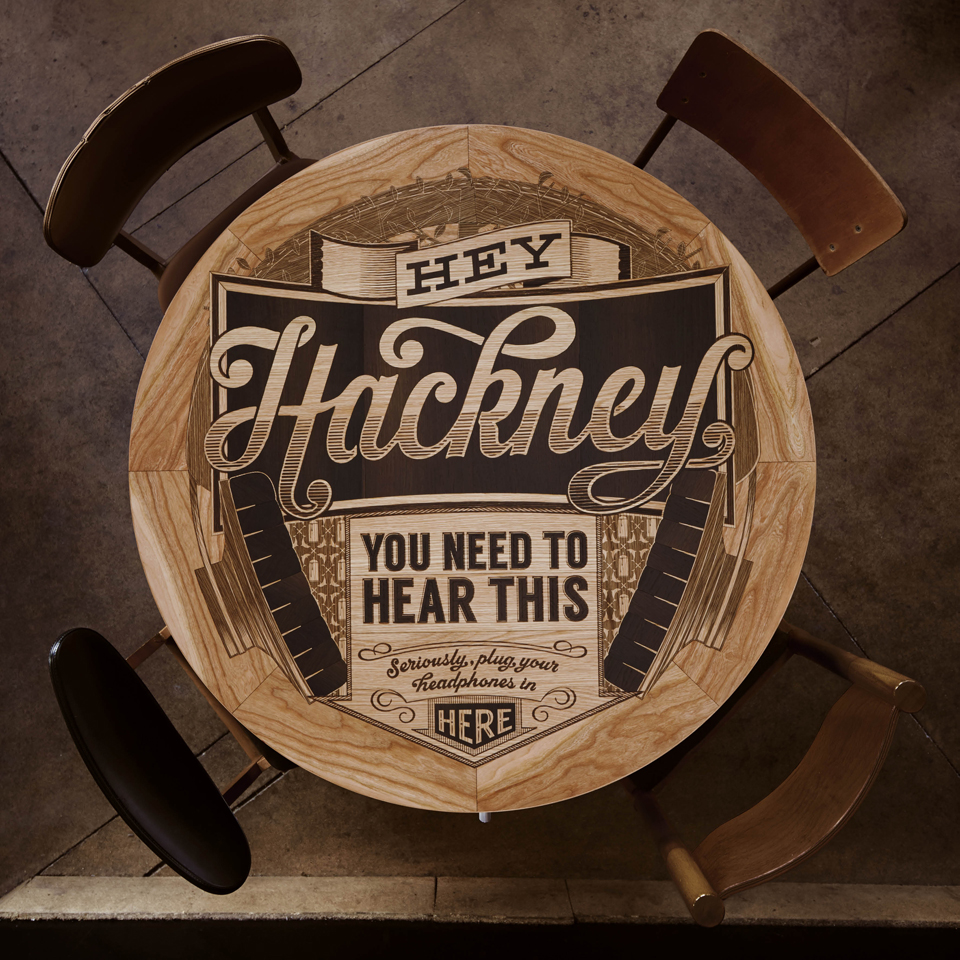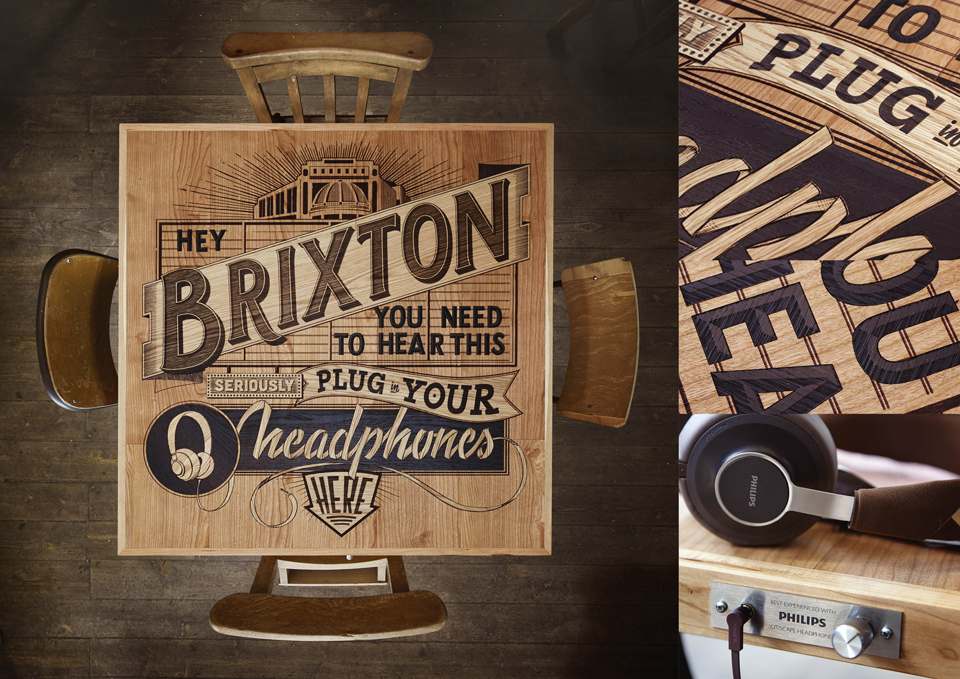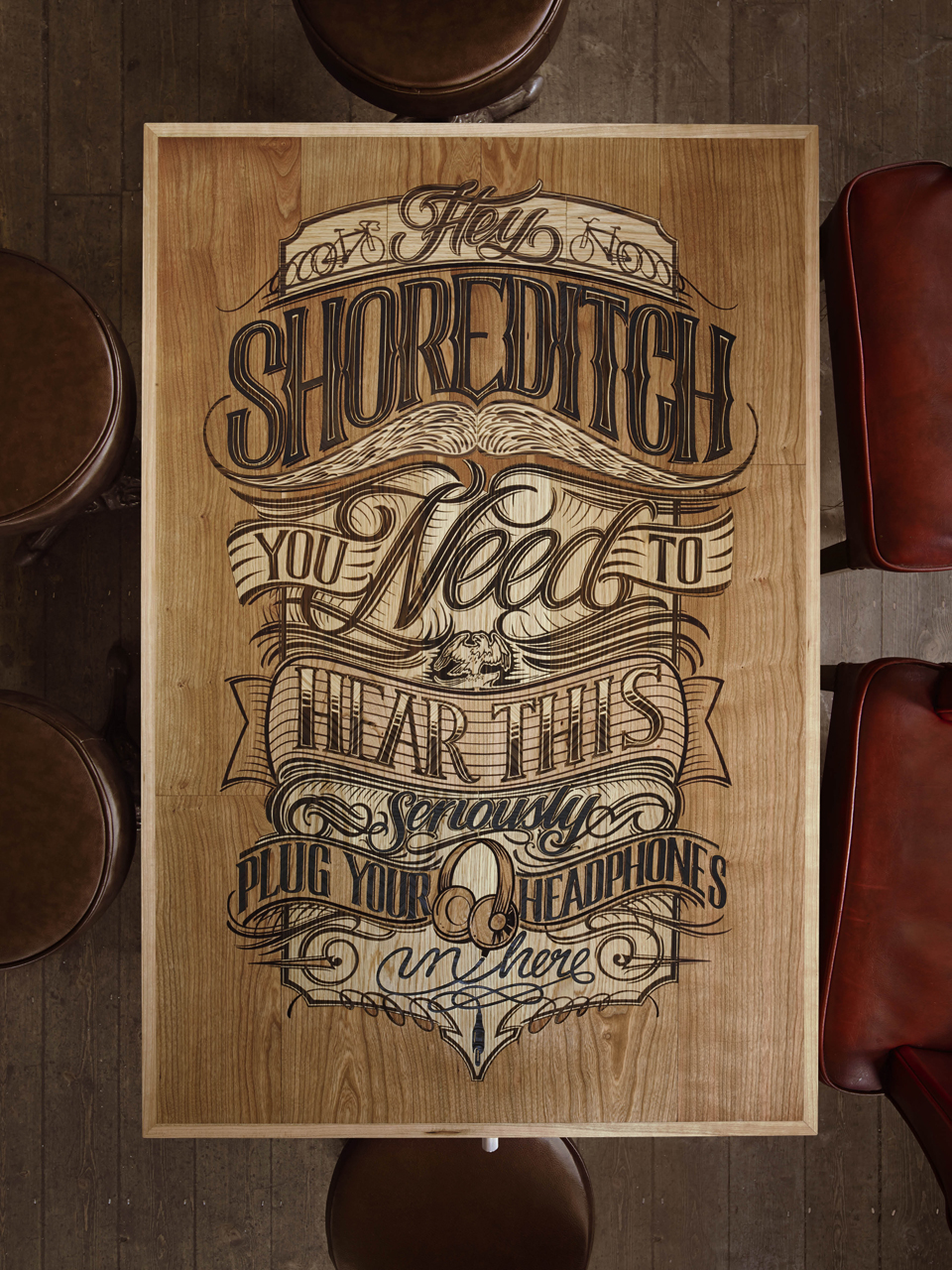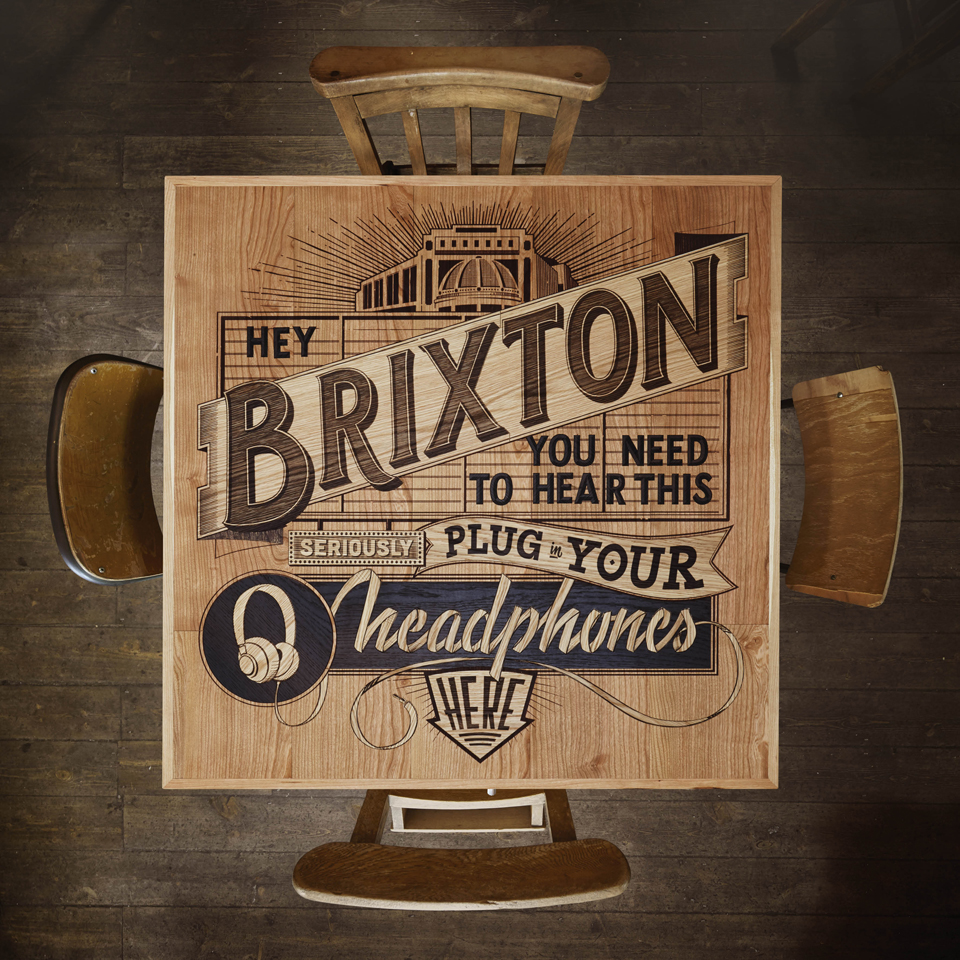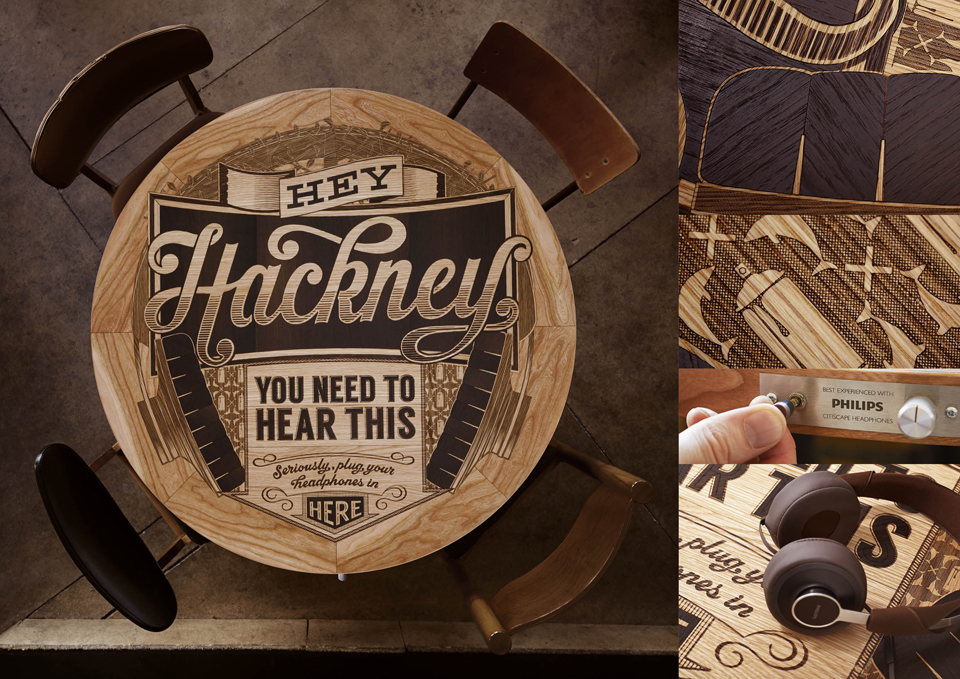
Ação da Philips une tipografia e cerveja em mesas que tocam música
Marca espalha mesas interativas por pubs de Londres para lançar novos fones de ouvido
Como parte da campanha e plataforma de conteúdo You Need To Hear This, a Philips criou uma série de mesas que tocam música para lançar seus novos fones de ouvido.
Espalhadas pelos melhores pubs do leste de Londres, tudo o que as pessoas precisam fazer é sentar nestas mesas especiais, embutidas com tocadores de músicas. Aos plugar nelas os fones disponíveis, é possível ouvir uma seleção de músicas feitas especialmente para a área em que o pub se encontra.
Cada mesa foi ilustrada à mão com tipografia e iconografia inspiradas pela região. A superfície foi trabalhada em diversos tipos de madeira, cada uma com técnicas diferentes incluindo marcenaria, corte à laser, madeira queimada e madeira talhada à mão.
A ideia foi desenvolvida em parceria entre Ogilvy & Mather, Noisey e Philips Headphones. As mesas são parte da fase piloto da ação, que continuará globalmente pelos próximos 12 meses.